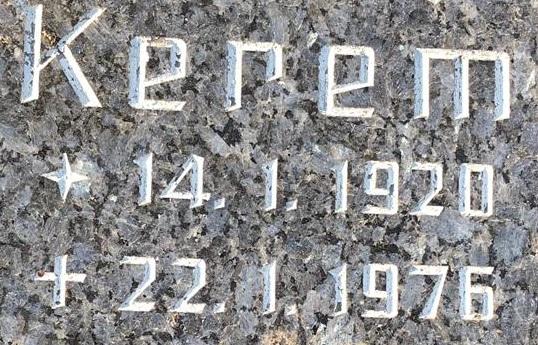
Suche Schriftart von einem Grabstein aus 1970er
kennt jemand die Schriftart die hier verwendet wurde??
Könnt Ihr mir diese nennen oder evtl. eine ähnliche Schriftart?
Aber Steinmetze sind ebebn auch klassische Schriftgestalter, da sie sich eben mit einiger Deduld einer Beschriftung widmen, die dann auch lange bestand hat. Hierduch sind eben auch Schriften nach solchen Steinmetzarbeiten entstanden, beste Beispiele, sie Ur-Antiqua, dies es als Trajan gibt, nach römischer Steinmetz-Arbeit an der Trajans-Säule, oder auch die Schrift Optima von Hermann Zapf, der die 1950 in Florenz nach einer Steinmetzarbeit skizzierte - auf einem 100 Lire-Schein.